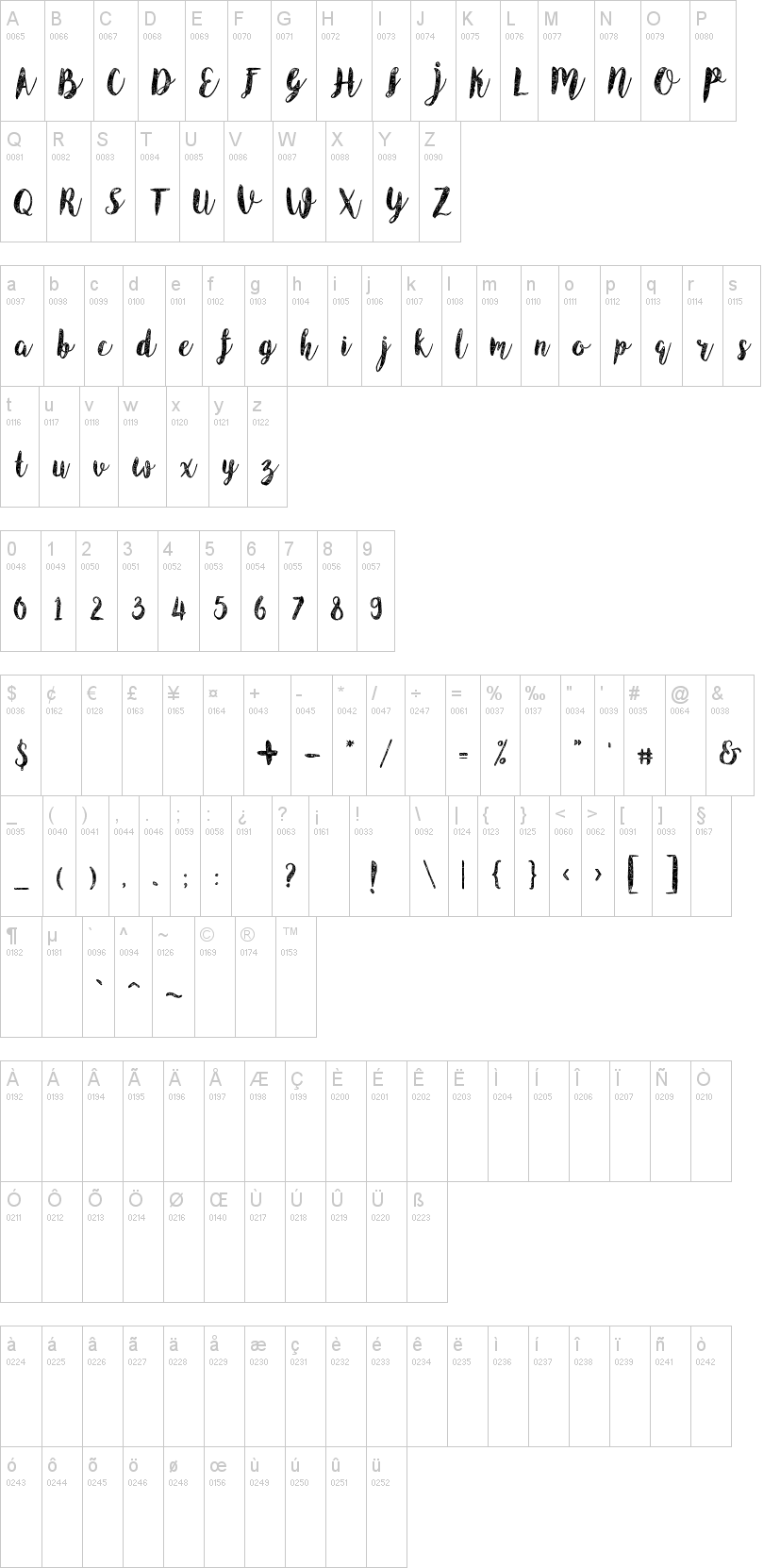
Angeline Vintage 是一款比较特别的字体,它具有经典的复古风格,拥有浓浓的古典气息。它的字体细腻,精致,让人感觉到一种温暖的古典气息。它的字体比较粗体,带有一定的古典风格,可以搭配大多数的文字,使文章更加生动有趣。它的字母具有浓厚的古典风格,可以给文章增添一种古典的气息,使文章更加耐看。内容介绍
Angeline Vintage是一款非常不错的手写艺术字体,具有很好的视觉感,适合于文化类的宣传设计、商业类品牌的广告和产品包装设计以及个性化文字排版等较多场景。